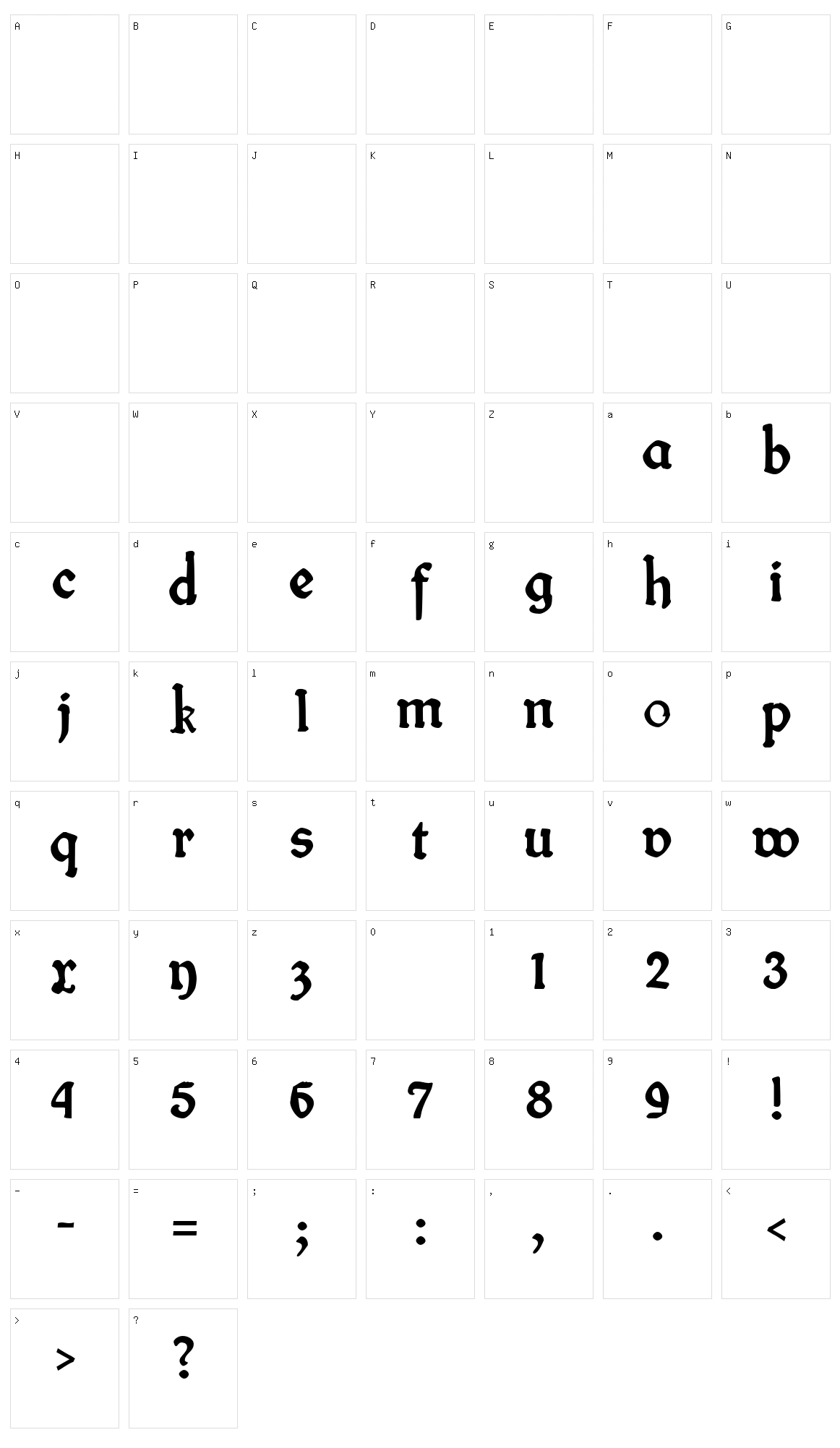
Fin Fraktur
Designed by: Intellecta Design
Category: Medieval & Gothic
FINFRAKTUR PW
set de minúsculas góticas, precedendo o estilo fraktur. sou fascinado pela beleza das minusculas, e esta fonte portanto só possui as mesmas.
Olá, sou designer gráfico especialista em identidade corporativa e logotipia. Mas o design e o estudo de tipologias e escritas cursivas caligráficas (históricas e contemporâneas) ocupam boa parte de meu tempo e predileções diletantes. Espero que tenha gostado desta fonte, um de meus primeiros trabalhos, que ainda estão sendo aprimorados.
FINFRAKTUR PW
gotic typeface, inspired in designs before the fraktur styles. how I like the beautiful of the minuskels this set contain only minuskel caps.
Hello, I am a graphic designer, specialist in corporate identity and logotipy. But the design and the study of typologies and calligraphic cursive writing (historical and contemporary) occupy a good lot of my time and dilettante predilections. I hope you like this font, one of my first works, which I am still improving.